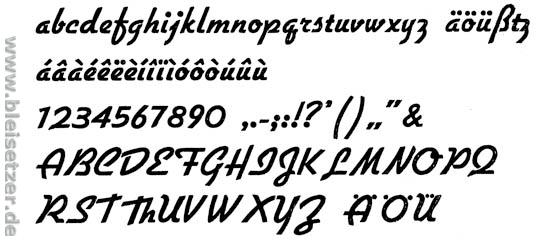
Suche Typo für Postkarte -> Tauchurlaub
ich muss für die Berufsschule eine Bestellpostkarte zum Thema "Tauchen in der Karibik" erstellen und bin mit meinem Slogan und Konzept auch soweit fertig, nur mein Problem ist jetzt dafür die passende Typo zu finden, da ich mit Urlaub und Karibik keine Schrift asoziiere und auch noch nichts passenden in den Schriftenpool unserer Firma gefunden habe.
Der Slogan lautet "Eine Welt voller Begegnungen...kann Ihnen nur ein Tauchurlaub mit Fly & Dive bieten."
Dazu benutze ich, unter anderen, folgendes Bild:
Ich würde mich sehr über ein paar Font Empfehlungen freuen.
eine Postkarte hat ein Format von DIN A6.
Ich befürchte, Dein Slogan ist zu lang.
So ein Slogan muß kurz und knackig sein,
sonst ist es keiner.
Dein Satz wäre geeignet als Subhead eines Artikels:
"Eine Welt voller Begegnungen...kann Ihnen nur ein Tauchurlaub mit Fly & Dive bieten."
Das hier wäre ein Slogan:
Fly & Dive - eine Welt voller Begegnungen
Oder:
Begegnungen der Dritten Art - Fly & Dive
Als Schrift würde ich persönlich zunächst einmal bei den kursiven Grotesken nachschauen. Das gibt der Schrift etwas dynamisches.
Oder wie wäre es mit der Schrift Flott:
So etwas findest Du sicher auch als Free Font irgendwo im Netz.